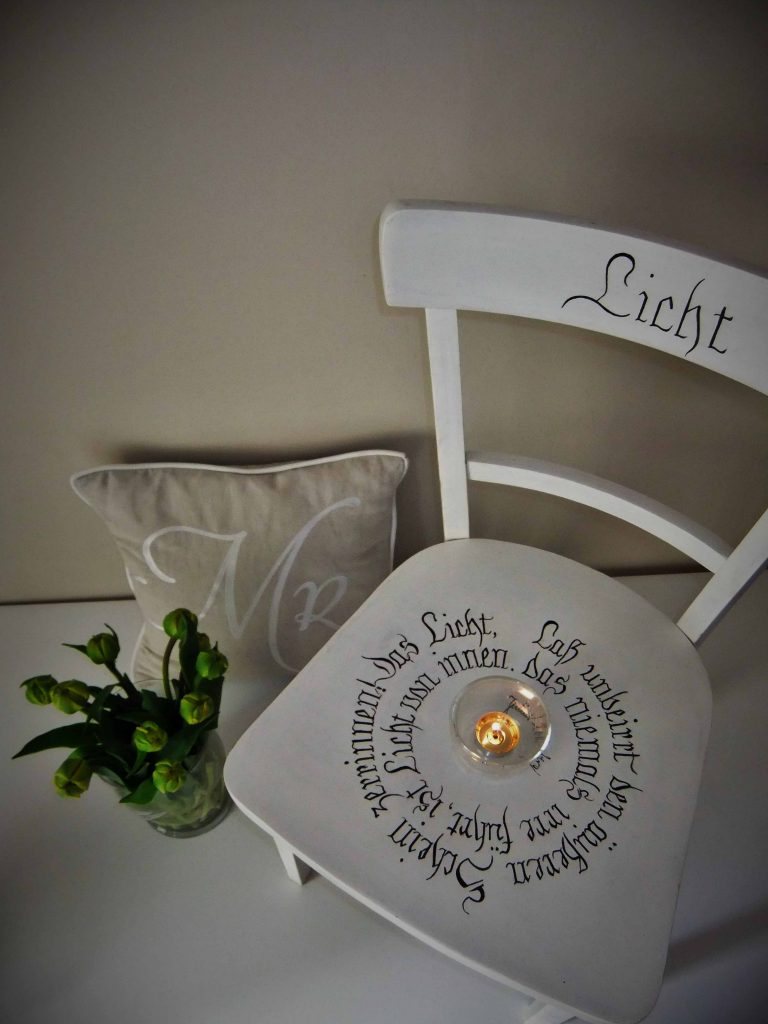
Aus Alt mach Neu – Kalligrafie auf Holz und Porzellan
Aus Alt mach Neu - Kalligrafie auf Holz und Porzellan: Es muss nicht immer Papier sein. Wie wäre es mit Worten auf einer alten Kiste oder auf Geschirr?
Aus Alt mach Neu – Kalligrafie auf Holz und Porzellan
Es muss nicht immer Papier sein, das man wunderschön beschriften kann. Wie wäre es mit
ein paar schönen Worten auf einer alten Kiste oder auf altem Geschirr?
Beim Durchstöbern von Trödelmärkten gerate ich regelmäßig ins Schwärmen, es gibt so vieles aus vergangenen Zeiten zu entdecken, alte Mehlsiebe in verschiedenen Größen, kleine Fußhocker mit geschwungenen Beinen, große, schwere Mangelrollen. An ihnen nagt der Zahn der Zeit, was ihren Charme ausmacht. All diese Dinge haben in der heutigen schnelllebigen Zeit einen ganz besonderen Reiz auf mich. So erzählen ihre Gebrauchsspuren oftmals ihre ganz eigene Geschichte und erinnern mich an Zeiten, in denen das Handwerk noch zählte. Meine große Aufmerksamkeit gilt alten Backbrettern, mal rund, mal eckig, Teigrollen oder außergewöhnlichen Holzkisten. Sie bieten, neben den oben genannten Dingen, eine schöne Fläche zum Beschreiben, um aus einem Flohmarktfund ein tolles Einzelstück zu machen.
Aufgetischt – eine Etagere aus altem Geschirr
Wer zu Hause noch Geschirr hat, was er nicht mehr braucht, kann daraus leicht und schnell eine dekorative Etagere zaubern.
Hierfür benötigt man: eine Tasse, drei Teller in unterschiedlichen Größen, eine Gewindestange, einen Diamantbohrer und ein wenig Malerkrepp. In der Mitte der Teller und am Boden der Tasse habe ich ein Loch von außen durch das Porzellan gebohrt. Damit dieses nicht abplatzt, klebe ich vor dem Bohren ein Stück Malerkrepp auf die Bohrstelle, auf die ich meine Markierung mit Bleistift zeichne. Sind die Löcher gebohrt, kann man die Teile ganz einfach zusammenbauen. Besonders schön finde ich, die Tasse als Kopf der Etagere, dort kann man ein paar Blumen hineinstellen. Damit die Etagere zum außergewöhnlichen Unikat wird, habe ich das Geschirr zuvor mit einem Gedicht beschrieben und danach im Ofen gebrannt – somit ist das Porzellan abwaschbar. Ob Gebäck, Pralinen oder lieber Knabberzeug, dieses schmückende Beiwerk sieht auf jedem Tisch toll aus.
Chalklettering – ein Backbrett wird zur Tafel
Chalkboards entdeckt man überall. Meist schmücken diese Kreidetafeln, opulent beschriftet und mit kleinen Illustrationen versehen, viele Cafés als Angebotsschild. Man kann sie abwischen und immer wieder neu beschriften. Für meine kleinere Variante habe ich mich für ein altes Backbrett entschieden, das ich erst angeschliffen habe, um eine glatte, saubere Oberfläche zu bekommen. Danach habe ich mit Malerkrepp einen Rand abgeklebt, diesen dann weiß gestrichen und die Fläche mit schwarzer Tafelfarbe zweimal nachgestrichen. Nach einer kurzen Trocknungszeit ist die Tafel nun fertig zum Beschreiben. Ein Lieblingsrezept, eine Botschaft für den Liebsten oder um darauf eine Einkaufsliste zu schreiben – diese Tafel ist vielseitig einsetzbar. Verschiedene Kreidestifte machen das Schreiben darauf kinderleicht. Tipp: Bringt man noch dekorative Haken an das Brett an, hat man gleichzeitig ein praktisches Schlüsselboard.
Ordnungshüter – eine Werkzeugkiste wird zum Zeitschriftenständer
Es gibt viele Verwendungsmöglichkeiten für eine alte Kiste. In diesem Beispiel habe ich mich dazu entschieden, eine alte Werkzeugkiste mit einem schönen Spruch aufzuhübschen. Auch dafür habe ich erst die Fläche angeschliffen, die beschriftet werden soll. Dafür sollte man die Länge des Spruches beachten, er darf nicht zu lang oder zu kurz sein. Es ist einfacher, diesen Spruch auf Papier vorzuschreiben, um dann die passende Schriftgröße zu bestimmen und bösen Überraschungen vorzubeugen. Bestückt mit Lieblingsmagazinen, wird daraus ein origineller und einzigartiger Zeitschriftenständer. Eine weitere Variante wäre, die Kiste mit Kräutertöpfen zu bepflanzen oder mit einer Beschriftung zu versehen. Das schmückt jede Fensterbank.
Bitte nehmen Sie Platz – der Stuhl bekommt ein neues Gesicht
Ein schlichter Stuhl muss nicht schlicht bleiben. Hauchen Sie einem alten Stuhl wieder neues Leben ein und machen Sie ihn zum Blickfang in Ihrer Wohnung. Dazu braucht es nicht viel, ein weißer Anstrich, ein Gedicht auf der Sitzfläche, darauf ein gemütliches Kissen oder eine Kerze in der Mitte und schon verleiht man einem alten Stuhl wieder neuen Glanz. Auch in diesem Beispiel sollten die Flächen vorher geschliffen werden, um eventuelle Unebenheiten auszugleichen. Da Rundgeschriebenes für mich eine besondere Herausforderung darstellt, schreibe ich den Text grundsätzlich mit Bleistift auf der Fläche vor, so kann ich leicht korrigieren, sollte ich mich verschätzt haben. Tipp: Es muss nicht „Schwarz auf Weiß“ sein, zarte Pastelltöne mit angeschliffenen Kanten verleihen einen schönen Shabby-Look.
Backe, backe, Kuchen – alte Teigrolle schön beschriften
Auf meinen Streifzügen über die Trödelmärkte haben es mir alte Teigrollen besonders angetan. Raritäten aus weißem Porzellan oder die klassischen Rollen aus Holz verwende ich immer wieder, um sie zu beschriften. Gern verschenke ich das ein oder andere Stück mit einem schönen Spruch darauf, liebevoll verpackt mit einem Kuchenrezept, handgeschrieben auf hochwertigem Papier und ganz individuell abgestimmt auf die Person. Wer damit anderen, so wie ich, eine Freude machen möchte, braucht neben der Teigrolle nur den passenden Stift. Mit Kreppband schafft man eine gerade Linie und kann den Spruch seiner Wahl darauf schreiben. So ein persönliches Mitbringsel hinterlässt mit Sicherheit einen bleibenden Eindruck.
Materialliste:
Kreidetafel
– Rico Design Tafelfarbe schwarz
– Stationary Island Chalk Marker D60 weiß
– Securit Chalk Marker 1-2mm weiß
– Swingcolor 2 in 1 Weißlack seidenmatt
– Schleifpapier, Malerkrepp